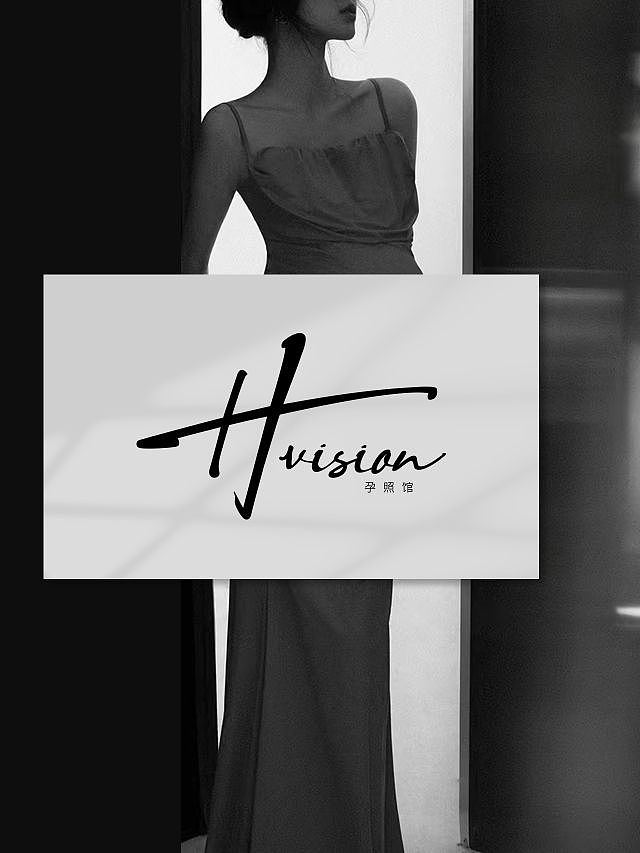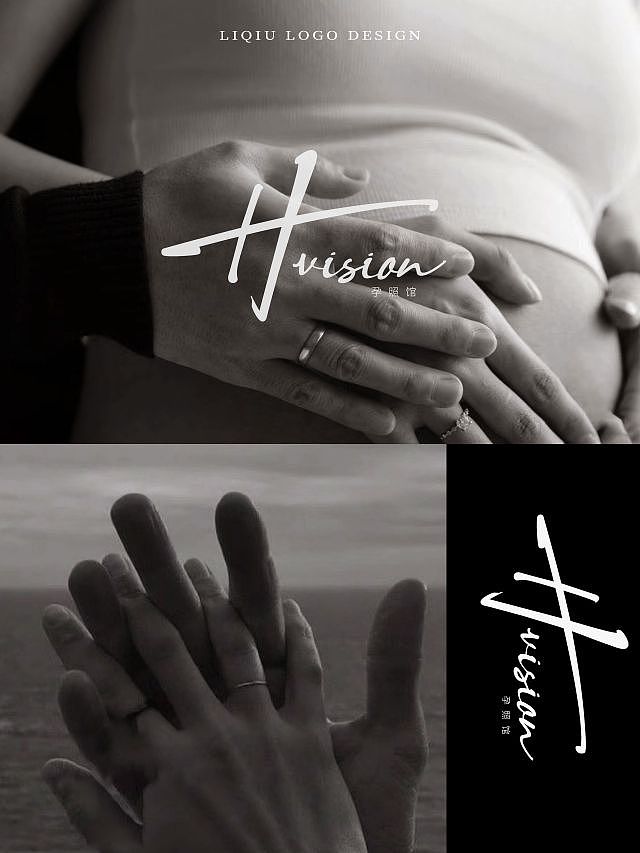
我不允许有人不知道手写字体logo的魅力!摄影logo设计
今日份摄影(孕照馆)工作室案例分享~
​手写字体logo设计的特点:
1.独特性:与计算机生成的字体相比,手写字体具有独有的笔画和风格,更具个性和独特性。
2.温暖感:人们往往认为手写字体更温暖、更人性化,更易于与观众沟通,能够建立更好的情感联
3.手绘感:手写字体有时候会带有一定的“手绘感”,能够营造更加自然、洒脱、随性的感觉。
​手写字体常用于婚庆品牌,艺术类品牌(咖啡、设计、服装品牌等)因为手写字体可以给人一种随性自然、野生洒脱的感觉,更符合品牌的视觉传达需求。